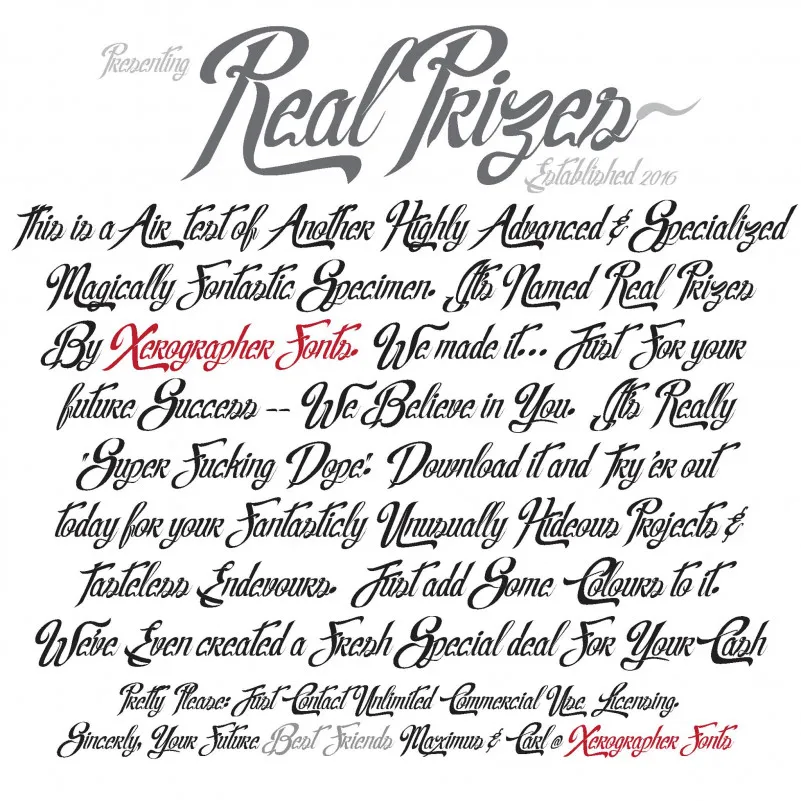
A fonte Real Prizes é uma deliciosa opção para quem busca letras elegantes e únicas para projetos pessoais ou até mesmo comerciais. Inspirada na arte do xingxing, que combina escrita chinesa e gráfica moderna de forma arrebatadora, esta família de fontes é perfeita para designers aficionados em calligrafia. Ideal tanto para trabalhos corporativos quanto para criações pessoais, Real Prizes oferece uma variedade de opções que se adequam a diversos estilos. Se você está procurando por um recurso gráfico elegante e versátil, esta fonte é uma escolha perfeita. A Hamilton, o designer dessa fonte sofisticada, garantiu um conjunto de letras sutis mas poderosas para atender a uma ampla variedade de projetos. Além disso, com opções para uso pessoal no valor de $25-$45, você tem acesso imediato à esta incrível família de fontes. Mas se desejar explorar as possibilidades comerciais e de licenciamento, não hesite em entrar em contato diretamente por meio do canal de comunicação escolhido: PayPal / Contact / Donate / Inquiries. Sem esquecer que seu pedido pode ser realizado através de qualquer um desses canais, criando conexões diretas com o designer para uma experiência de uso ainda mais personalizada e divertida.